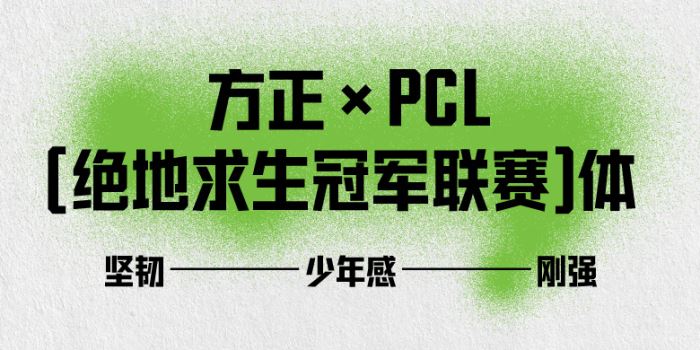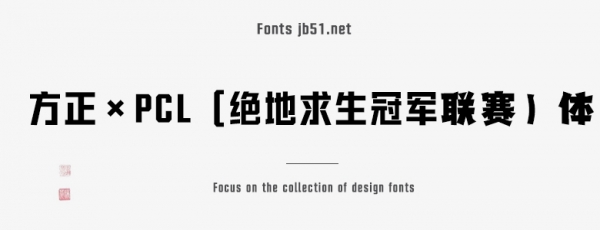
方正×PCL(絕地求生冠軍聯(lián)賽)體由方正字庫(kù)曹基殿設(shè)計(jì)師出品的藝術(shù)字體,字體平刷圓潤(rùn)入筆,運(yùn)筆時(shí)整體橫畫(huà)較細(xì),保持文字的筋骨,適合應(yīng)用于藝術(shù)設(shè)計(jì)、平面宣傳設(shè)計(jì)、網(wǎng)頁(yè)設(shè)計(jì),書(shū)法等領(lǐng)域。
該字體”是由方正字庫(kù)和絕地求生冠軍聯(lián)賽共同打造的一款充滿少年感、具有團(tuán)隊(duì)協(xié)作精神、整體風(fēng)格硬朗、性格剛強(qiáng)的創(chuàng)意黑體字。整體字形內(nèi)部結(jié)構(gòu)方正緊密、布白均勻、避讓有序使字體擁有簡(jiǎn)潔干練、堅(jiān)韌牢固的特點(diǎn)。與傳統(tǒng)平切設(shè)計(jì)不同,此款字體將底部?jī)A斜的筆畫(huà)做了斜切處理,讓筆畫(huà)更加硬氣、使字體具有書(shū)寫(xiě)感,同時(shí)增添昂揚(yáng)無(wú)畏的少年氣息。